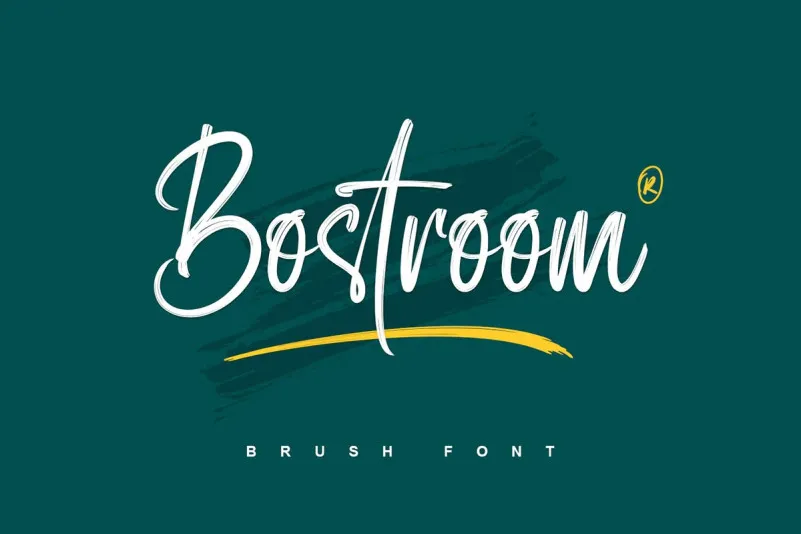
Bostroom Font – Download Grátis
A Bostroom Font é uma fonte script ousada que se destaca por seus traços esfuziantes feitos rapidamente com pincel e uma linguagem distintiva, criada para um leque de projetos diversos. Seja para logotipos e branding, convites ou materiais de correspondência, designs de casamento, publicações em redes sociais, anúncios, embalagens dos produtos, desenhos dos produtos, selos, fotografia ou até mesmo os marcos especiais das celebrações — a Bostroom Font tem o poder de dar vida ao seu design. Seja qual for o propósito do projeto que você tenha em mente, a Bostroom Font certamente será sua fonte ideal.